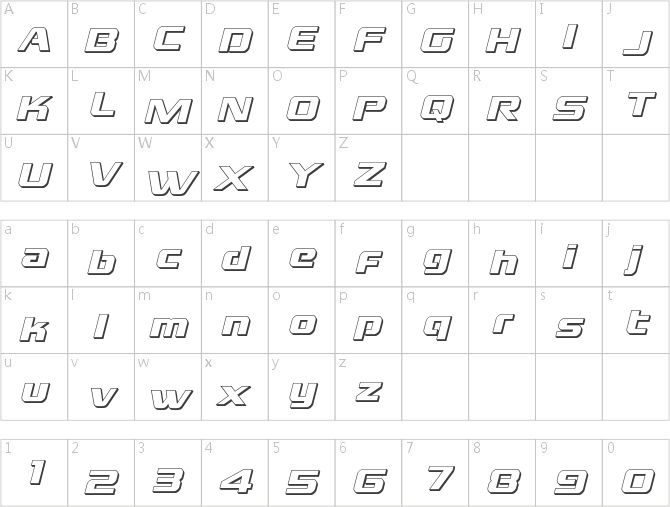
Grand National 3D Italic
Grand National 3D Italic介紹
Grand National 3D Italic字體字庫是一款讓人賞心悅目、百看不厭的英文字體,適合各類廣告和產品包裝設計應用,字體大小0.04MB,格式為ttf字體,上傳用戶是手機洗相,作者/版權方為未知